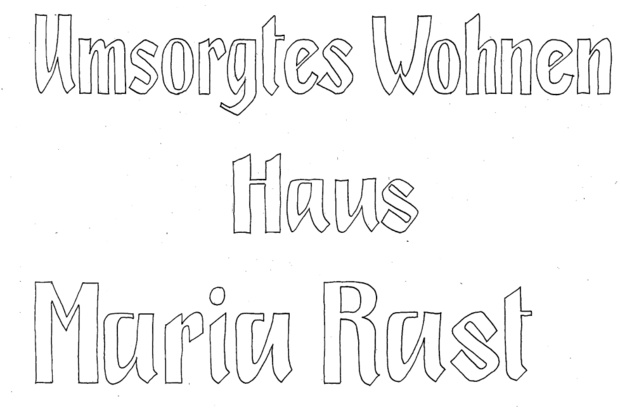
Schrift von Skizze gesucht.
Hab da eine Vorlage einer Architektin, die ein Altersheim umbaut, das auch beschildert wird. Hat eine Vorlage von der Leitung dort bekommen. Mit der Schrift soll die Beschilderung ausgeführt werden. Kann mir jetzt nicht vorstellen, daß das jemand ohne Vorlage aus dem Handgelenk geschüttelt hat. Scheinbar ist diese Vorlage aber nicht zu organisieren. Weiß jemand, welche Schrift hier als Vorlage gedient haben konnte?
Kann mir jetzt nicht vorstellen, daß das jemand ohne Vorlage aus dem Handgelenk geschüttelt hat.
Die Skizze sieht aber genau danach aus. Ich denke, dass du allenfalls ähnliche Schriften finden wirst.
Selbst ähnlich dürfte schwierig werden – das ist schon sehr speziell. Wie alt ist das Haus denn? Selbst wenn man einrechnet, dass diese Grafik vielleicht nur eine schlecht abgemalte Version der ursprünlichen Buchstaben ist, dann spricht immer noch einiges dafür, dass das irgendwann mal ein Schildermaler vor Ort konstruiert/geschrieben hat.
Vielleicht haben die dort in dem Heim ja noch weitere Beispiele dieser Schrift, die die Rekonstruktion erleichtern würden?
Genügten (vorerst) auch die Buchstaben, die in den Beispielen vorkommen.